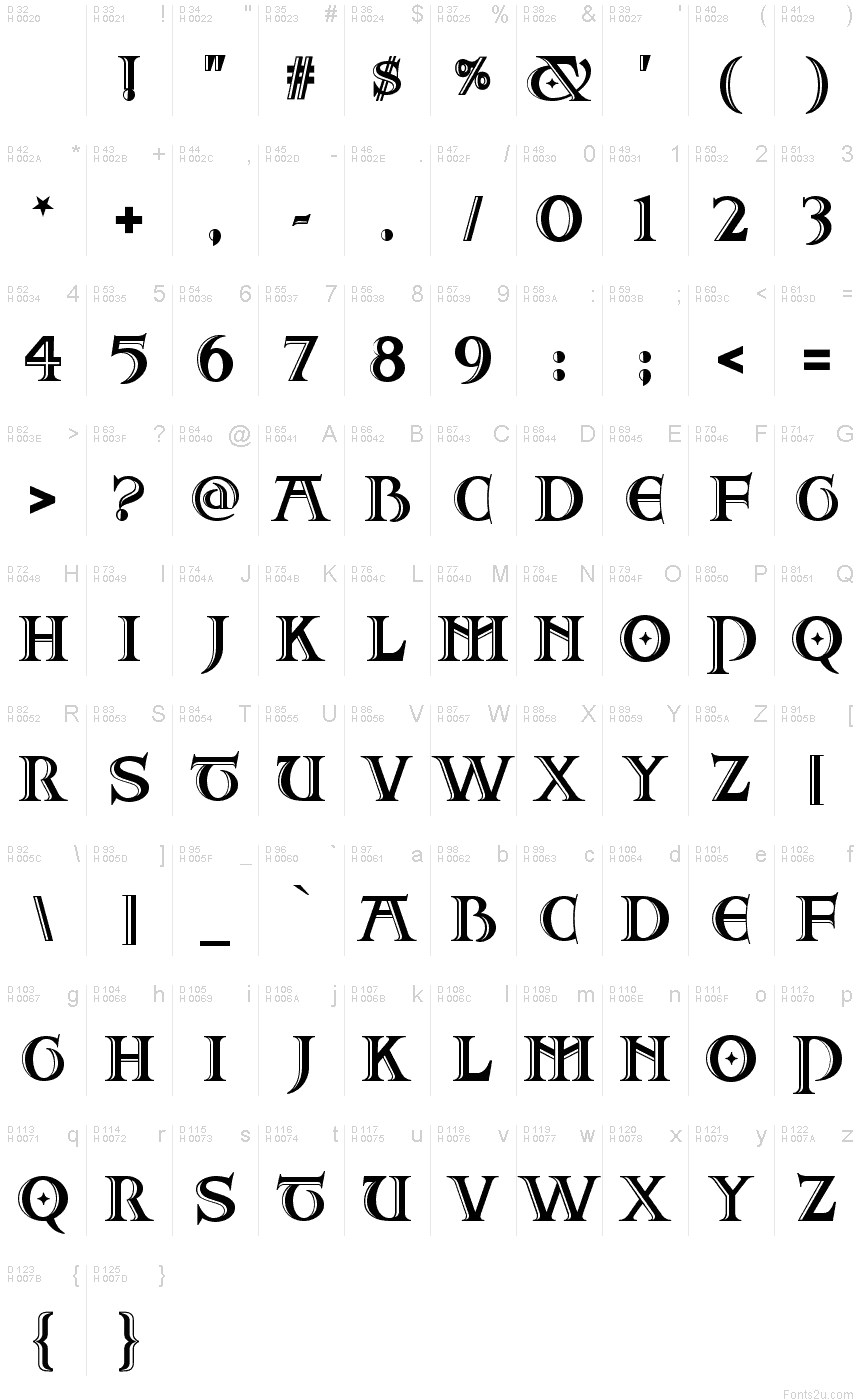
TwoForJuanNF
Two For Juan NF, di Nick Curtis, è un carattere display gotico vittoriano gratuito, con lo stile audace dei vecchi cartelli pubblicitari. Le lettere mescolano tratti larghi ad alto contrasto con grazie divise e ricurve e forme interne strette, dando all'intero design un ritmo d'altri tempi che risulta teatrale senza mai essere troppo carico.
Si adatta perfettamente a packaging vintage, insegne in stile saloon, locandine di eventi, copertine di libri e titoli d'impatto, dove la sagoma decorativa è in grado di reggere la scena da sola. Essendo un font gratuito, è l'ideale anche per monogrammi, iniziali e marchi brevi, specialmente se cerchi quel look inciso tipico del Vecchio West senza ricorrere a effetti di invecchiamento.